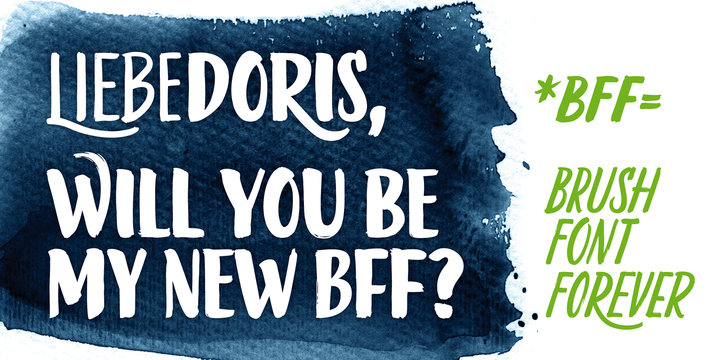
A fonte ‘LiebeDoris – 4 Fonts’ pertencente à categoria de Brush Fonts foi criada pelo designer Hamilton. Inspirado por uma sessão especial com o pintor de sinais icônico Mike Meyer, Ulrike do site de fontes LiebeFonts buscou desenvolver um tipo de letra versátil e encantadora para as placas de sinalização. Este projeto revolucionário resultou em uma série de quatro tipos de letras não convencionais, cujo estilo é capaz de capturar o realismo de um cartaz autêntico pintado a mão. Como se fossem os próprios caracteres, estas letras evocam a essência única e singular dos anúncios de lojas devidamente personalizados. A fonte ‘LiebeDoris – 4 Fonts’ oferece um conjunto de quatro tipos diferentes para escolher, cada um com suas características únicas, perfeita para adicionar um toque único e autêntico a qualquer projeto. Este tipo de letra não apenas combina em harmonia com outros materiais gráficos, mas também permite que você faça um design verdadeiramente inovador e distintivo.